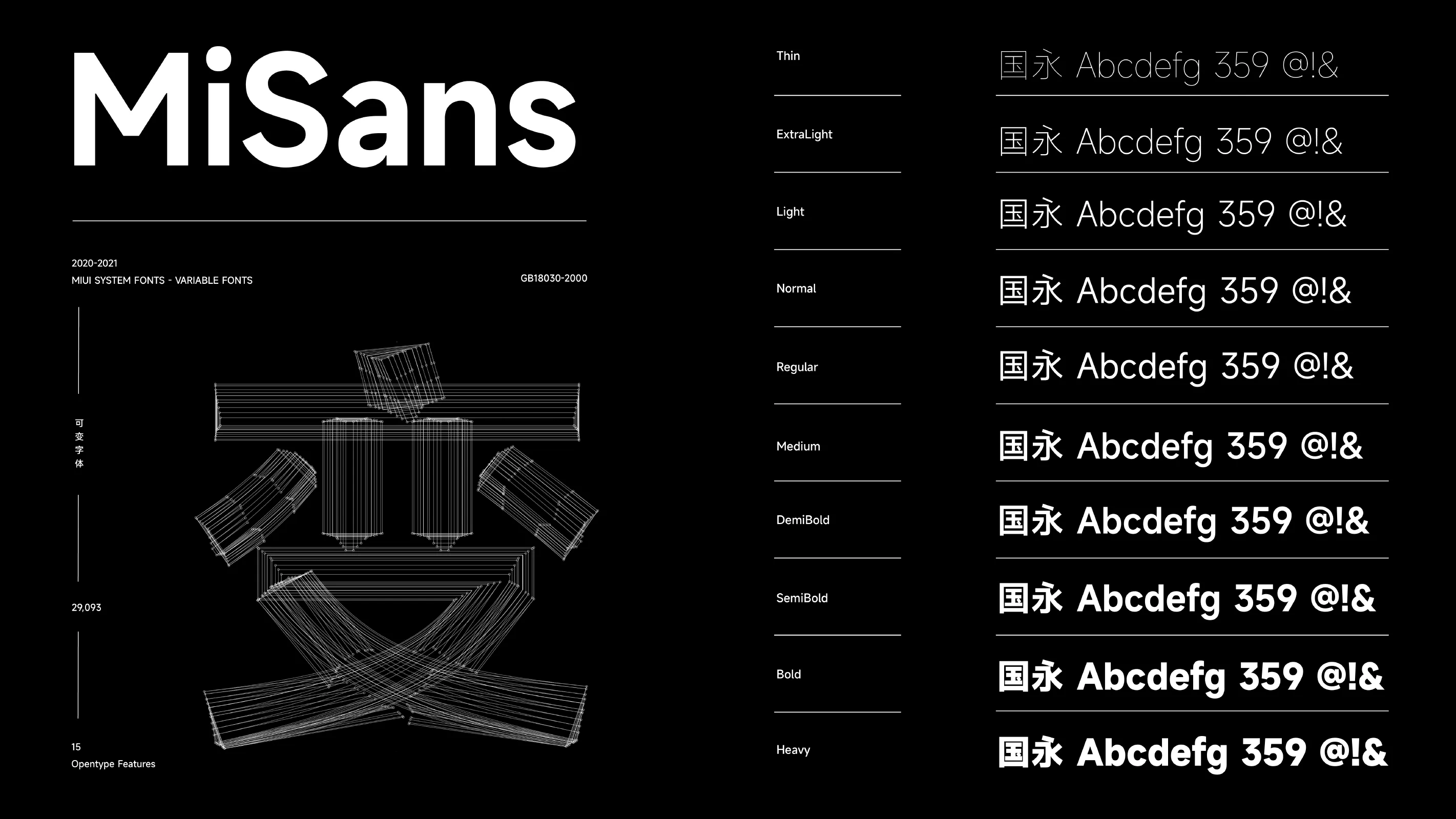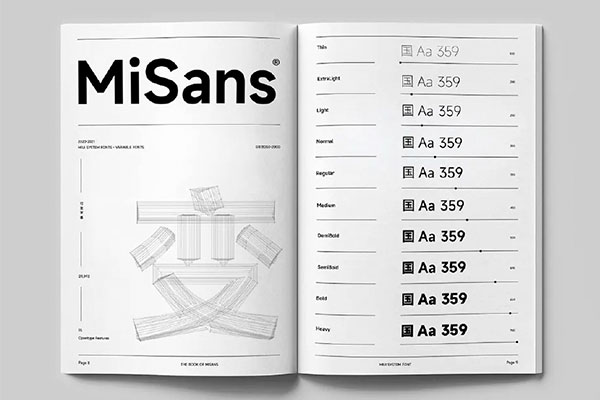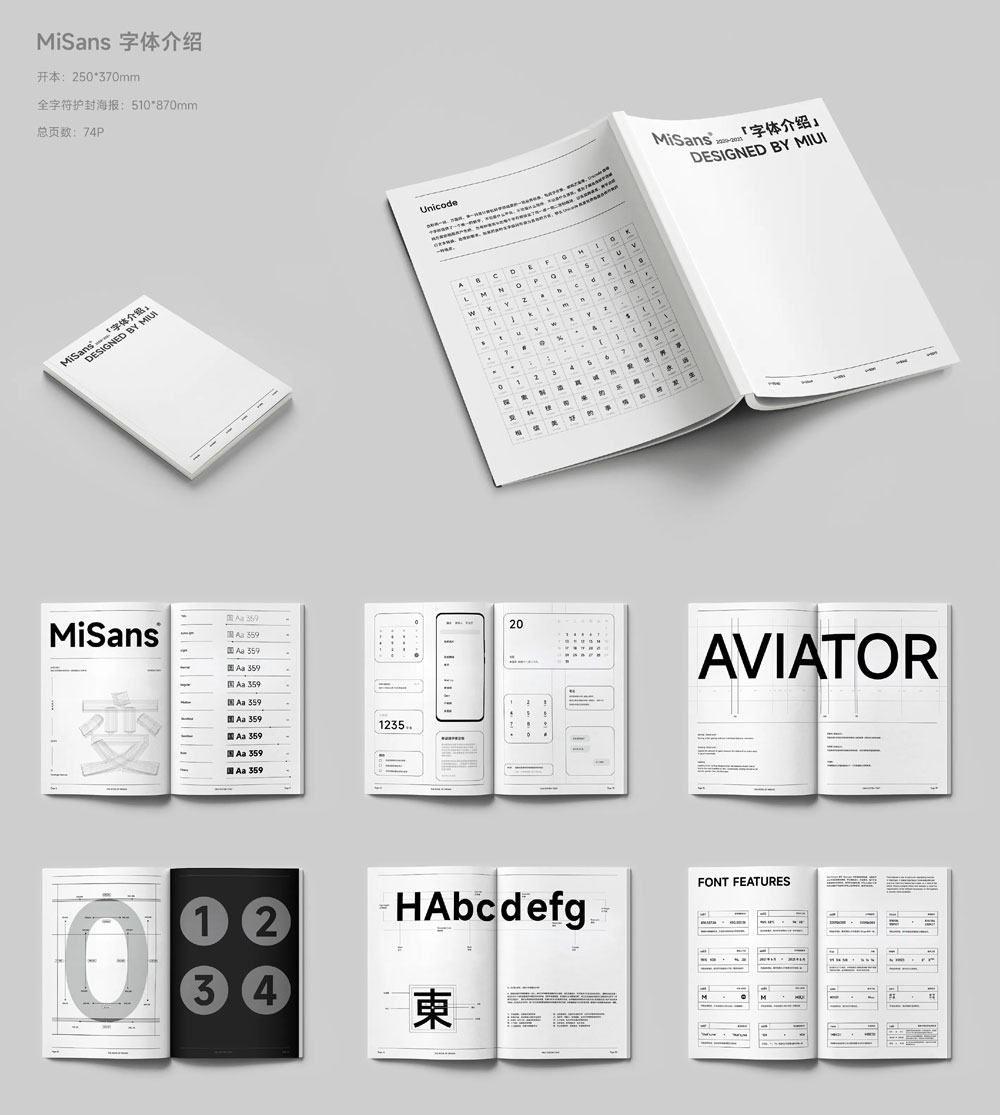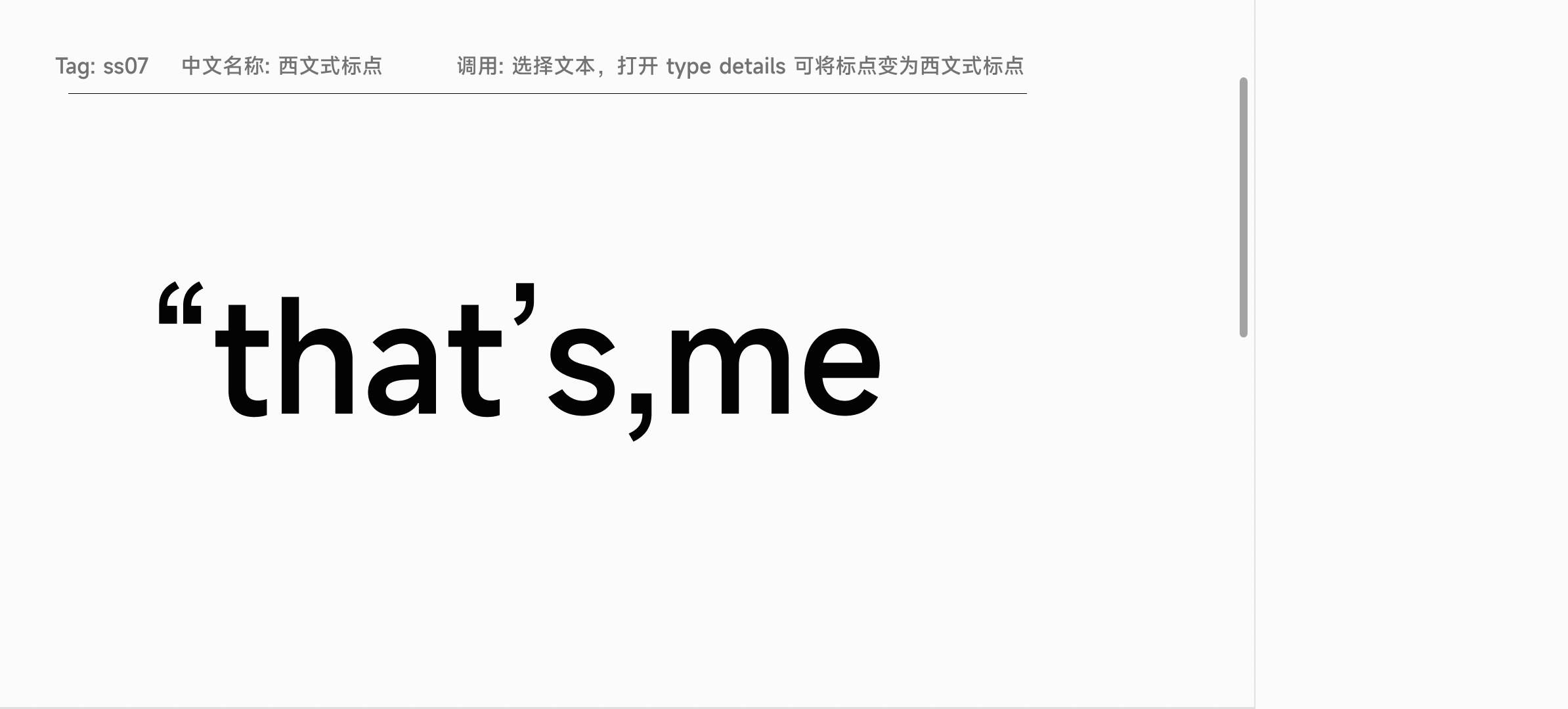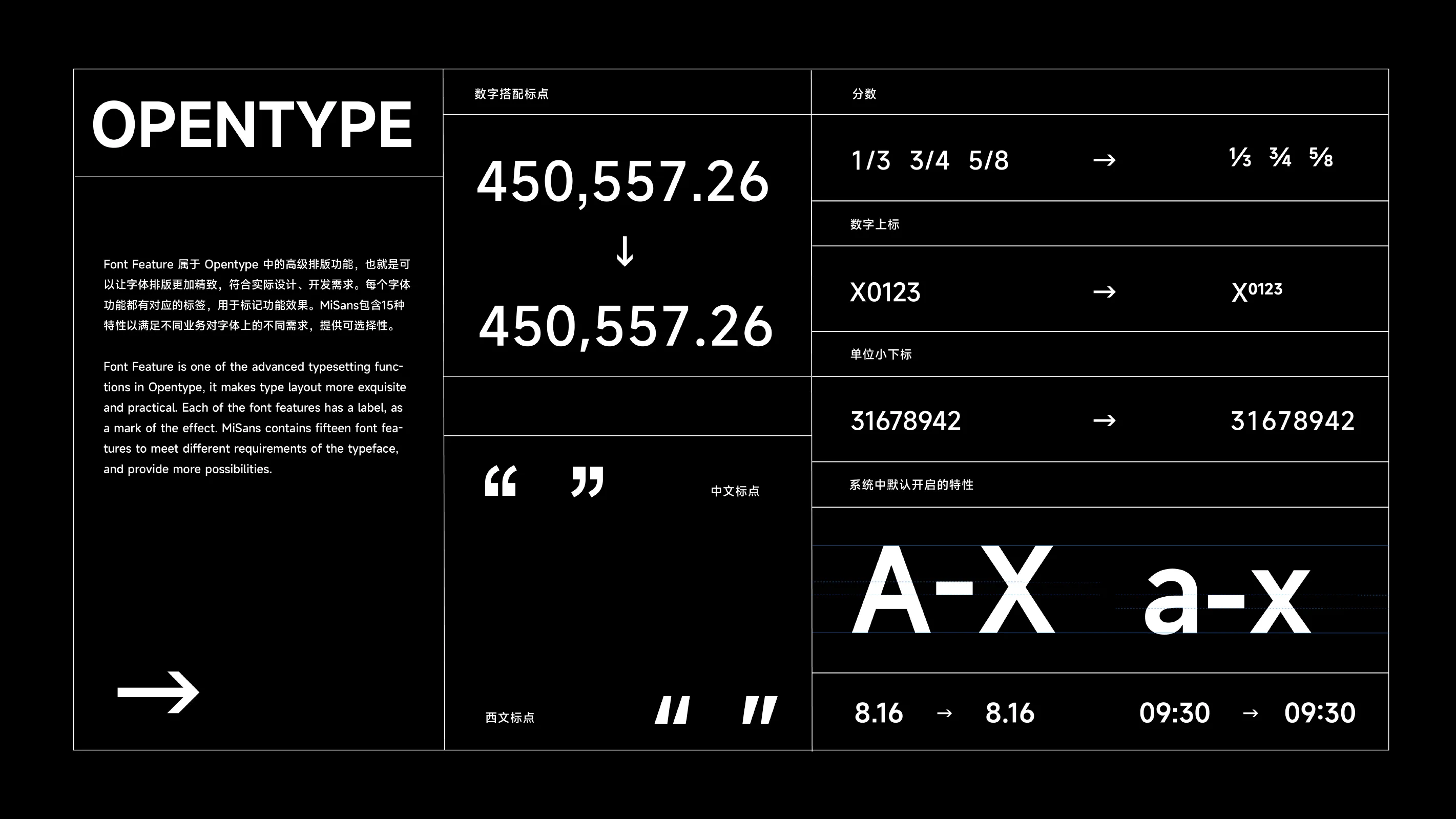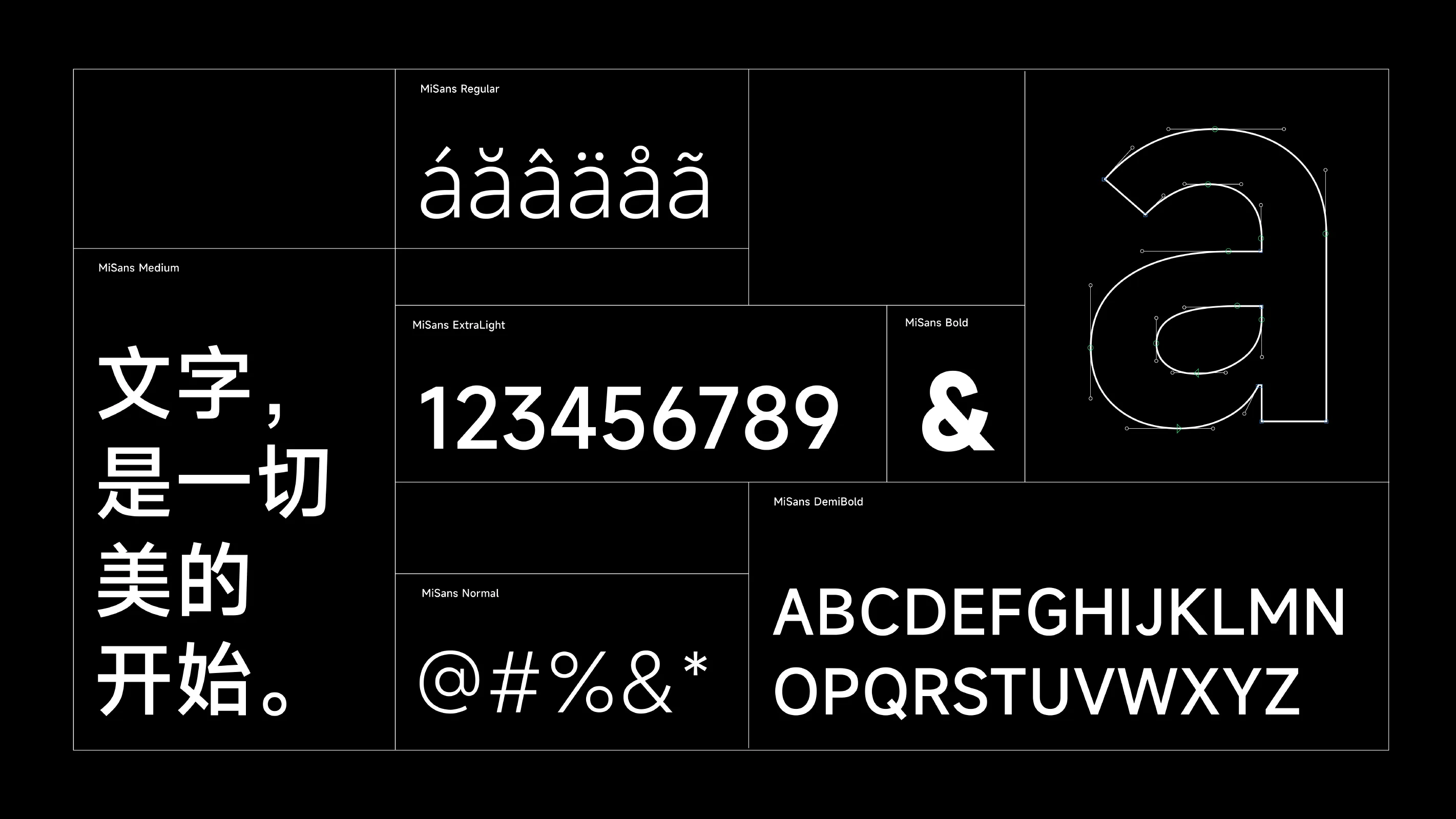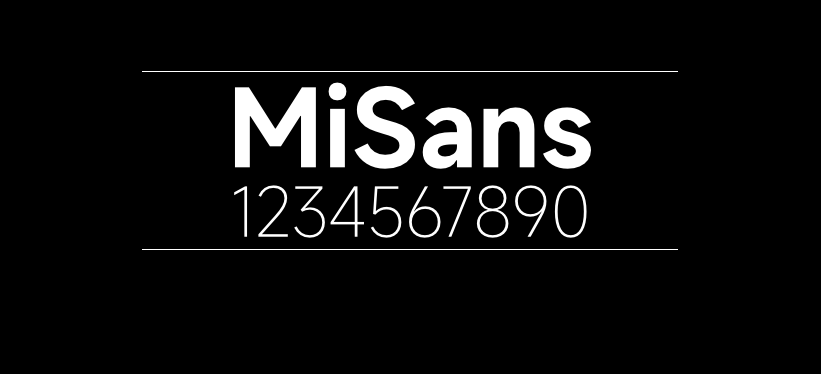
MiSans
MiSans是小米公司最新推出的MIUI 13内置的全新系统字体,随系统一起发布,供全社会免费商用。
Misans笔型平直有力,设计更加简约,减少视觉负担,更有利于屏幕显示。共包含29,093个字符,支持多种语言。MiSans 提供了多种 OpenType 功能,可根据特定需求来选择不同形态的字符,例如某些标点符号可以根据周围字母的形态自动调整至合适的位置。MiSans字重齐全,层级清晰,拥有10个字重,实力大厂出品,质量无需怀疑,赶紧下载吧!
字体功能调用及实现
font-feature 属于 Opentype 中的高级排版功能,也就是可以让字体排版更加精致,符合实际设计、开发需求,可根据特定设计需求选择不同的字体形态。大部分软件都可以通过 Opentype 面板访问此功能。
(部分特性在MIUI系统应用中不会默认生效)
以figma为例